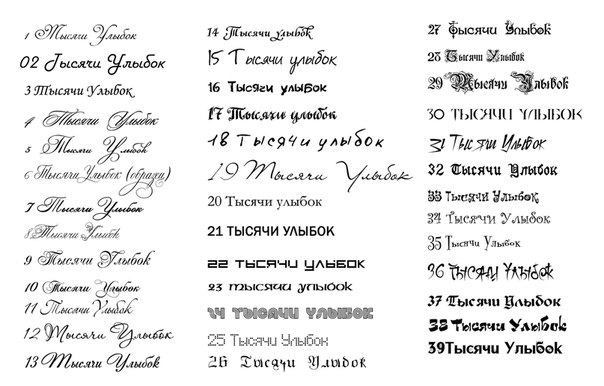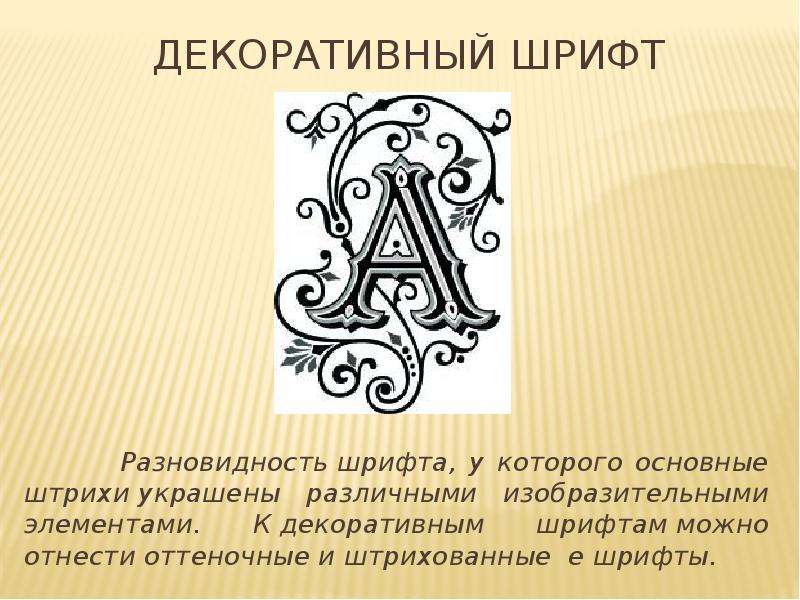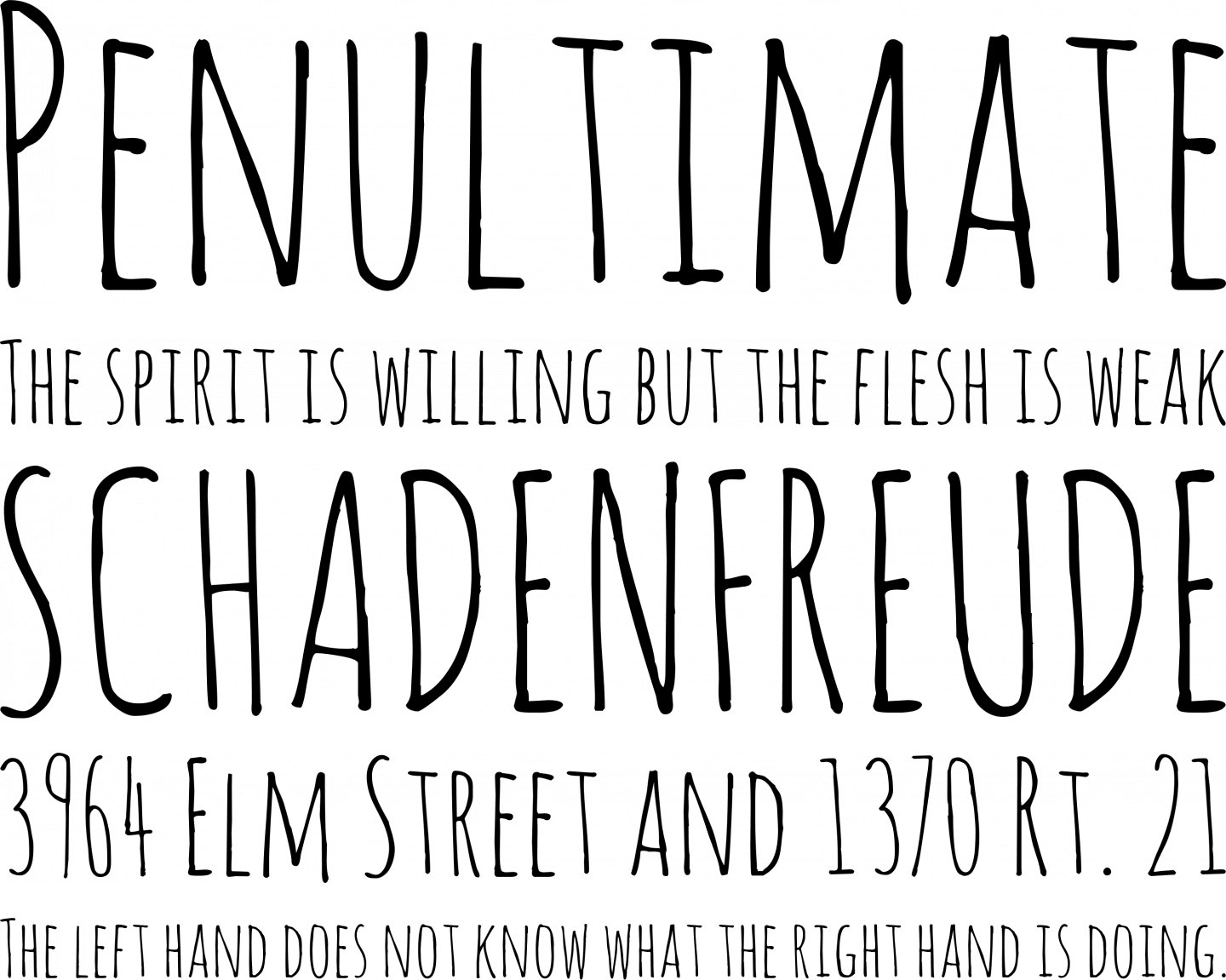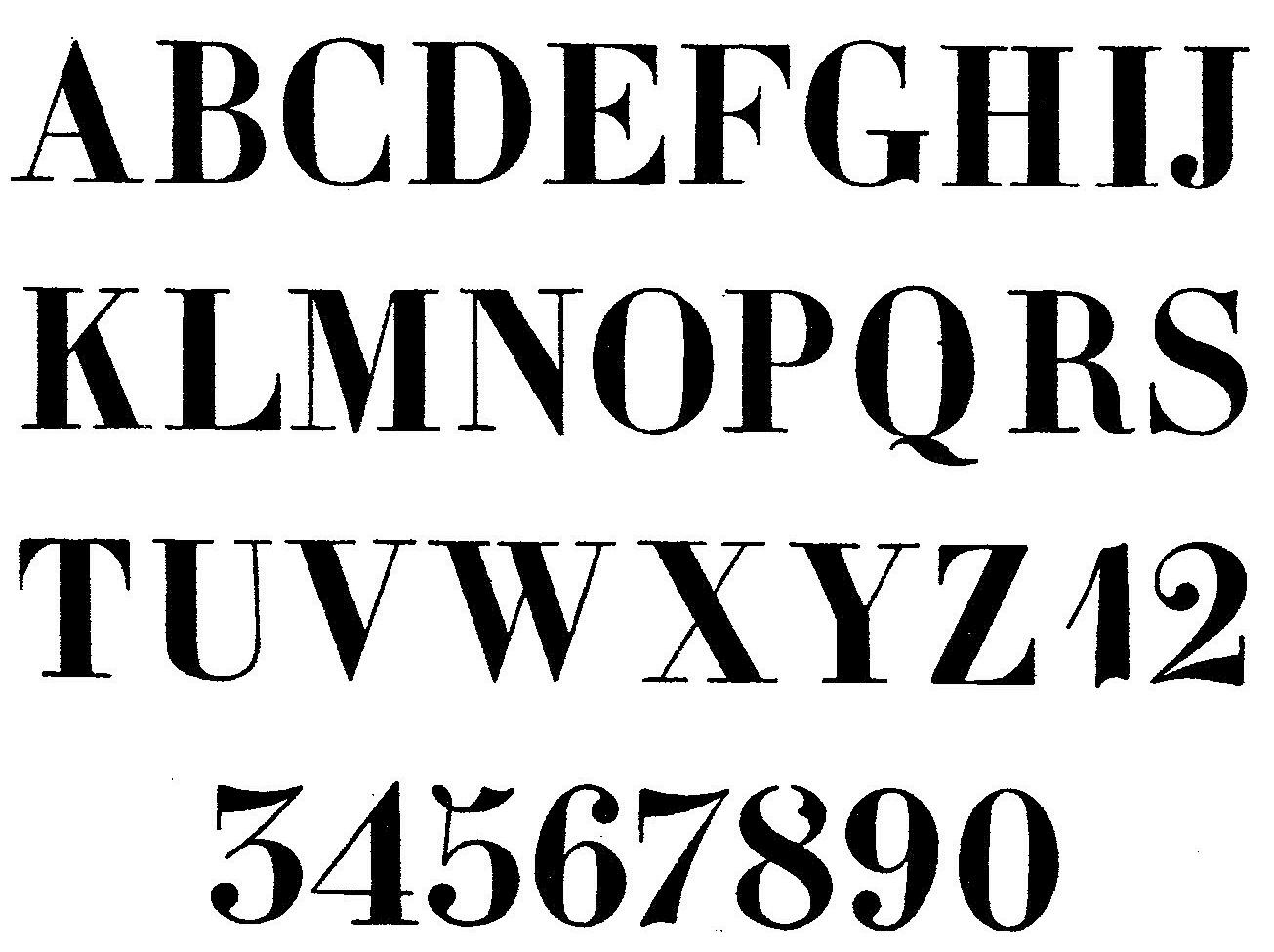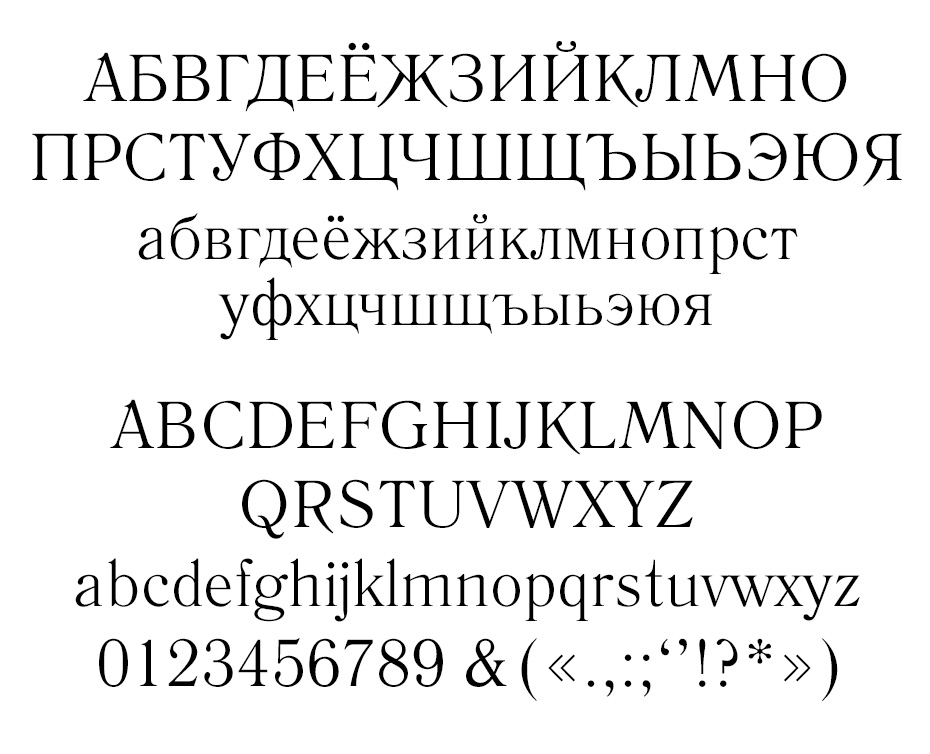
Что такое шрифты — их виды и классификация с примерами
Узнаете, что такое шрифты и каких видов они бывают. Разберем их классификацию и анатомию строения. Покажу, какими лучше пользоваться, а какими нет. Также будет много примеров того, как выглядят шрифты и чем они отличаются.
Что такое шрифты
Шрифт является основным элементом типографики. Здесь часто возникает путаница. Потому что шрифтами люди называют, как сами шрифтовые файлы на компьютере, так и шрифтовые семейства, которые доступны в редакторах.
Шрифты для компьютера и печатных изданийШрифт — это некая совокупность знаков. То есть букв, цифр, символов, знаков препинания и так далее. Все они были спроектированы для совместного применения.
А то, что мы видим на своей рабочей странице правильно называть не шрифтом, а гарнитурой.
Гарнитура — это шрифт определенного рисунка. Или говоря иначе семейства шрифтов. На английском это определение называется «typeface».
А вот комплект букв и знаков (то есть шрифтовой файл) — это физическое воплощение гарнитуры шрифта в компьютерных кодах.
Гарнитура шрифта на бумагеПо английски шрифтовой файл называется «font».
В общем, шрифт — это то, чем печатают. В классической типографике это были металлические или деревянные буквы. А гарнитура, это то, что мы видим на бумаге или экране.
Хотя здесь сложно избежать путаницы. Потому что в графических редакторах меню шрифтов называется именно словом «font».
Это неправильно!
Ведь там отображаются не шрифтовые файлы, а их начертания. То есть семейства шрифтов или гарнитура.
Характеристики шрифта
Давайте рассмотрим основные характеристики шрифта. Первое важное понятие, это базовая линия. Нетрудно заметить, что в строках текста, буквы расположены на невидимой линии. У разных шрифтов высота положения этой линии может различаться.
Базовая линия шрифта нужна чтобы управлять интерлиньяжем (межстрочным расстоянием).
Интерлиньяж выражается в пунктах. Он измеряется от базовой линии одной строки, до базовой линии следующей.
Единица измерения шрифта
Еще нужно сказать о системе измерения, которой пользуются в типографике.
Независимо от основных единиц измерения, которые приняты в стране (дюймы или метрическая система), в типографике принято пользоваться типометрической системой.
Не нужно путать ее с метрической!
В типометрической системе используется не миллиметр, а типографический пункт. Это такая единица измерения шрифта.
В российской типографии принят французский типографический пункт. Он составляет 0.376 мм. Еще существует англо-американский пункт. А в программе верстки используется пункт от компании Adobe. Он равен 1.72 дюйма или 3.352 мм.
Именно по этой причине текст современных печатных изданий может отличаться по размеру текста, набранного тем же кеглем и шрифтом, но в докомпьютерную эру.
Кегль
Кегль — это размер шрифта. Изначально он определялся высотой кегельной площадки литеры.
Кегельная площадка литеры служит основой для относительных единиц измерения в типографике. Ее понятие идет из докомпьютерной эры. Тогда каждая буква отливалась в виде отдельной металлической литеры.
Металлическая литераПрямоугольная площадка, на которой находилась буква на торце литеры, называлась кегельной площадкой. А сама буква (ее отпечаток) называется очком литеры.
По бокам от него находились правый и левый полуапроши. Они задавали промежуток между знаками.
И хотя в компьютерном наборе, литеры, как таковой не существует. Все же понятие кегельной площадки сохранилось.
Когда мы выбираем букву в графическом или текстовом редакторе, то выбирается не сама буква, а место под кегельную площадку.
Кегельная площадкаНа рисунке, это прямоугольная площадка.
Она гораздо выше средней строчной буквы.
Это потому, что высота кегельной площадки приблизительно равна сумме высоты строчных букв. А также верхних и нижних выносных элементов.
Кегль шрифта или сам размер тоже измеряется в пунктах.
Размер шрифта
Помимо кегля, впечатления о размере шрифта создается размером его строчных букв. По английски эта величина называется «X-Height».
Это потому, что этот размер определяется, как расстояние от базовой линии шрифта до вершины строчной английской буквы «X».
А линия, проведенная на высоте этой буквы и параллельные базовые линии шрифта, называется средней линией (Main Line).
Но здесь нужно понимать, что при одном и том же значении кегля, физический размер строчных букв у разных гарнитур может отличаться.
Можно написать одно и тоже слово два раза. К примеру, один шрифтом Times New Roman, а второй Helvetica.
Мы выставили одинаковый размер кегля. Но тем не менее, визуально размер этих шрифтов отличается.
Виды шрифтов
Теперь давайте вспомним, какие бывают виды шрифтов. Как они делятся, на какие группы и категории. Все шрифты делятся по разным признакам. Ниже мы их и рассмотрим.
Но что если читаемость текстов не очень-то и важна? Например, для бренда, который коммуницирует с аудиторией через Instagram, используя визуальные образы. В таких имиджевых случаях стоит обращать внимание на образ, который вызывает шрифт. Может быть, здесь всё наконец-то субъективно? Попробуем разобраться.
Для описания шрифтов и их классификации существует много различных параметров. Остановимся на нескольких принципиальных.
Засечки и их отсутствие
Пожалуй, самый очевидный пункт, который понятен абсолютно всем.